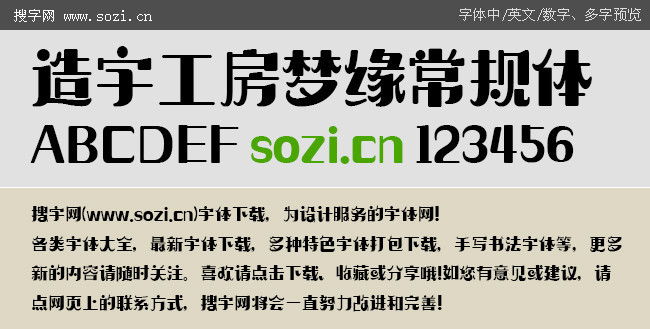
造字工房夢(mèng)緣常規(guī)體
搜字網(wǎng)提供一款造字工房夢(mèng)緣常規(guī)體中文藝術(shù)字體下載,造字工房夢(mèng)緣常規(guī)體字體個(gè)性鮮明,筆畫粗細(xì)對(duì)比強(qiáng)烈,個(gè)別點(diǎn)畫變形為圓形,撇、捺的處理跳脫流暢,極富動(dòng)感。此款字體適用于兒童讀物、報(bào)刊雜志標(biāo)題、廣告設(shè)計(jì)等領(lǐng)域。